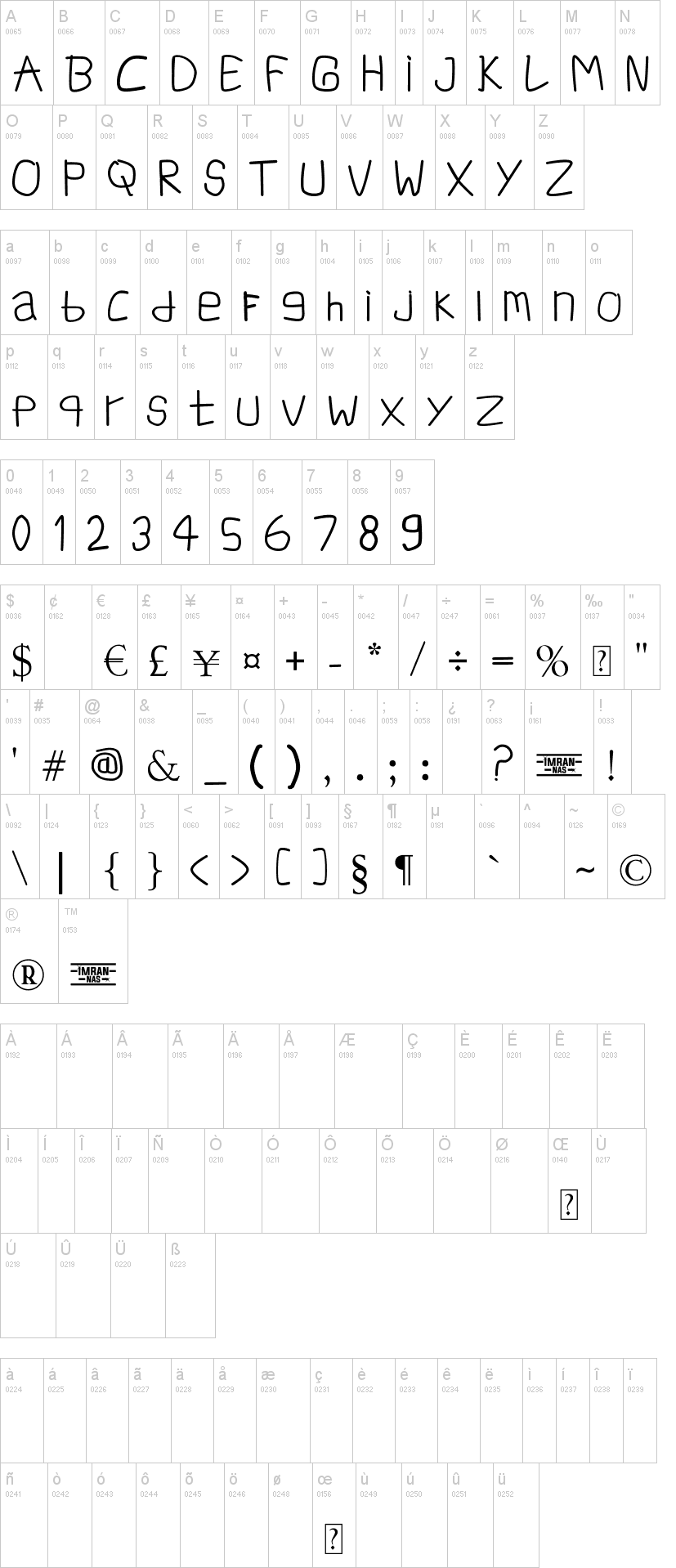
INF Simpang Ampek
? INF Simpang Ampek字体是一款非常特别的英文字体,它采用了传统的马来文书写风格,将英文字母改写成马来文字符,以更加精美的方式描绘出字母的外形。这种字体有着独特的设计,可以更好地表现出文字的灵动与精致。它可以让文字看起来更加精致,有着更加丰富的表现力。
INF Simpang Ampek是一款非常不错的手写艺术字体,具有很好的视觉感,适合于文化类的宣传设计、商业类品牌的广告和产品包装设计以及个性化文字排版等较多场景。
INF Simpang Ampek字符映射图